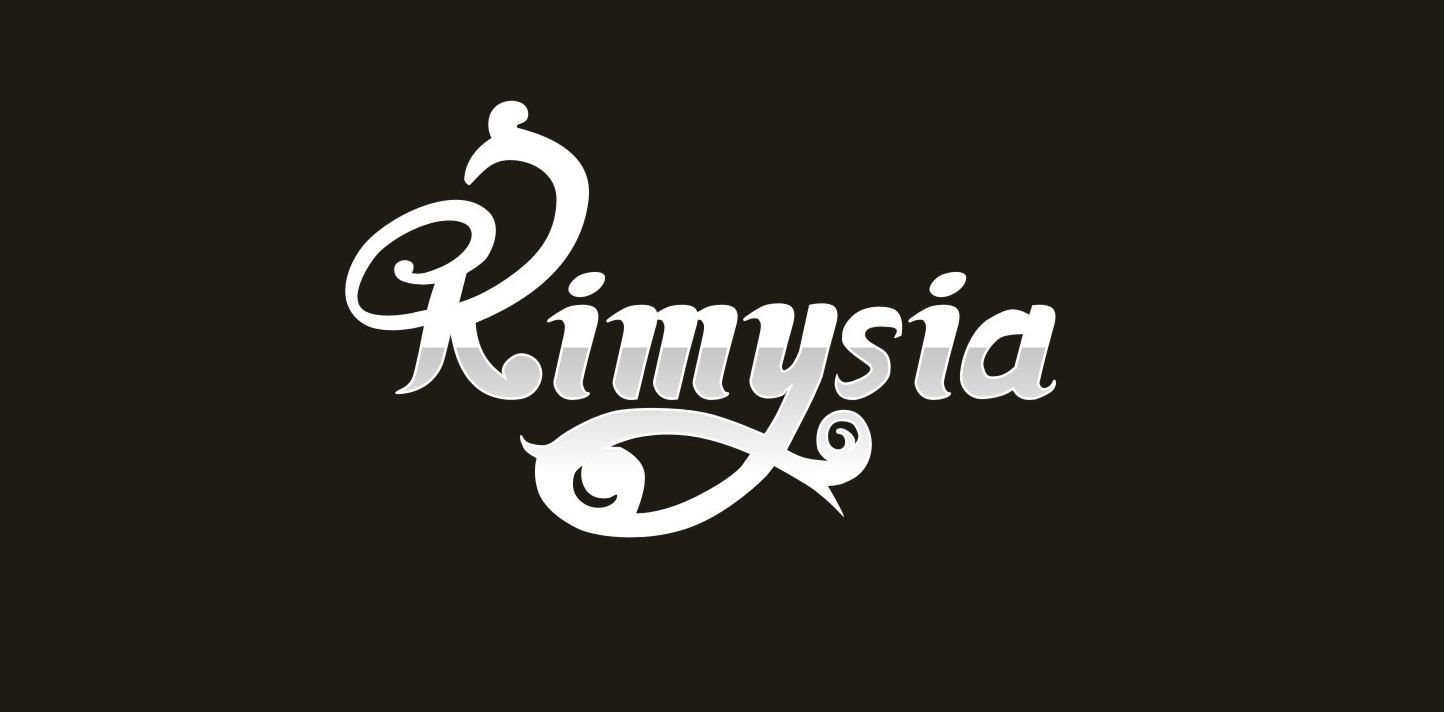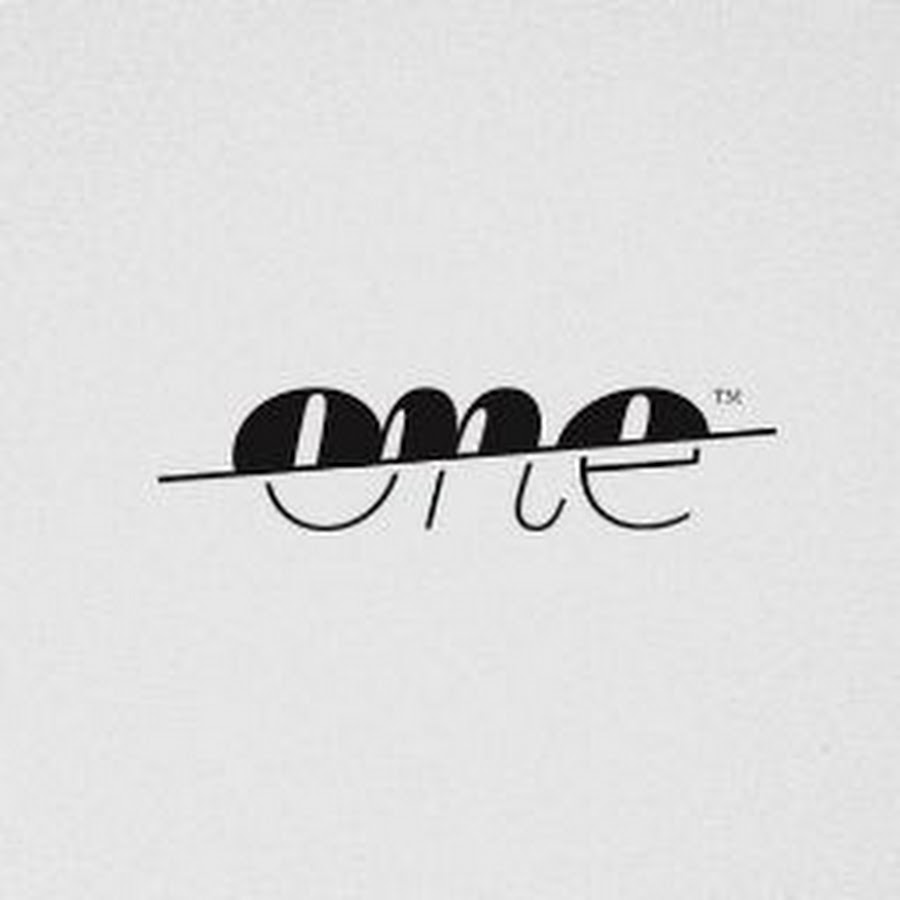
Выбор шрифта для лого: по одежке встречают
Каждая шрифтовая гарнитура индивидуальна и имеет собственное настроение. Она может быть серьезной или легкомысленной, элегантной или строгой. Но какую бы вы не решили использовать при создании логотипа, она должна отражать месседж бренда. Предлагаем немного полезной информации и практических заметок, которые помогут избежать ошибок при выборе.
Почему это важно
Подбор шрифта для логотипа сродни выбору одежды для выхода в свет. В зависимости от внешнего облика, окружающие делают вывод о личности, ее стиле, социальном положении, возрасте (реальном, или том, на который хотелось выглядеть). Для различных ситуаций и случаев подходит различная одежда. Скажем, на интервью будет неловко в купальнике, а на пляже – в галстуке.
Шрифты задают тон, по которому складывается первое впечатление о дизайне и бренде в целом. Поэтому так важен продуманный выбор и правильное определение цели: куда мы идем — на пляж или интервью? Элементы шрифта дополняют друг друга или не соответствуют друг другу? Эффективно ли они передают те свойства, которые вы вкладываете в проект?
В процессе дизайна нужно принять во внимание множество факторов.
Ошибки в выборе будут отвлекать потенциальных клиентов от вашего месседжа и намерений. Итак, с чего же начать? В первую очередь, нужно разобраться с основными понятиями.
Виды шрифтов
Существует множество классификаций шрифтов по историческим или техническим признакам. Описать их в одной статье не представляется возможным, поэтому сфокусируемся на четырех основных категориях, которые помогут в выборе подходящего шрифта для конкретного дизайна.
Шрифты с засечками.
Отличаются наличием черточек в конце основного штриха буквы. Эти шрифты выглядят более серьезными, символизируют надежность, уважение к традициям, комфорт. Примеры: Times New Roman, Trajan, Baskerville, Georgia Italic.
Рубленые шрифты – это шрифты без засечек
Смотрятся изящно и современно, транслируют аккуратность, четкость, инновационный подход. Примеры: Helvetica Bold, Franklin Gothic, Calibri, Myriad Italic.
Считается, что засечки повышают удобство чтения больших напечатанных участков текста, направляя движение глаз вдоль строк.
В то же время, засечки, как правило, очень маленькие и тонкие, поэтому не всегда корректно отображаются на компьютерных экранах. По этой причине шрифты с засечками часто применяются для печатных изданий. Если речь идет об использовании на Интернет-порталах, дизайнеры выбирают рубленые гарнитуры.
Шрифт Frutiger был разработан в 1975 году и использовался для указателей в аэропорту Шарль де Голля (Франция). Также он используется в швейцарских паспортах.
Рукописные шрифты
Имитируют чей-то почерк или каллиграфическое написание. Все буквы, как правило, соединены. Эта категория используется в различных стилях: как в элегантном, так и непринужденном. Вызывает ассоциации с креативным мышлением и нежностью. Примеры: Bickham Script, Edwardian Script, Lavanderia.
Классический пример удачной типографики – Cadbury. Лого напоминает подпись Уильяма Кедбери и с 1921 года практически не менялось
Декоративные шрифты
Разрабатываются с целью привлечь внимание. Как правило, удобочитаемость уступает место привлекательности, поэтому они могут использоваться лишь в небольших количествах и для конкретной цели.
Такие шрифты выражают эмоциональное богатство, уникальность и дружелюбность. Примеры: Cooper, Spaceage Round, Valencia, Giddyup.
Что учесть при выборе
Первый критерий при выборе шрифта – соответствие вашей цели. Перед тем, как начать поиск на компьютере или в Интернете, подумайте, что именно вы хотите донести аудитории, какие свойства и качества свойственны бренду. Не поддавайтесь первому желанию остановиться на чем-нибудь забавном или экстраординарном, не давайте волю личным приоритетам. Думайте о бренде в целом.
Рукописное лого популярной платформы для электронных рассылок MailChimp отражает неформальный стиль и дружественный интерфейс, формируя общее мнение о бренде в целом.
Также стоит заранее подумать о контексте и аудитории. Например, если ваш логотип будет использоваться в визитках, то шрифты должны быть читабельными даже при очень маленьком размере. Если ваша аудитория – пользователи соцсетей, часто просматривающие сайты на смартфонах, то гарнитура должна быть удобной для маленьких экранов.
Очень важно понимать и возраст ваших читателей.
Шрифт Bodoni хорошо известен, благодаря логотипу Vogue. Он выглядит очень эстетично, благодаря засечкам и контрасту между толстыми и тонкими линиями.
В целом, показатель читабельности очень важен. Имеет значение размер шрифта и размер строчных букв. Также важно межбуквенное расстояние – оно может упростить чтение. Если есть пространственные ограничение, то можно выбрать специальный оптимизированный шрифт.
Логотип FedEx был разработан еще в 1994. Внешне простой шрифт Univers подобран настолько удачно, что выглядит свежо и спустя пару десятилетий. Его дизайн вызывает ассоциации с высокой скоростью (доставки отправлений) и устойчивостью.